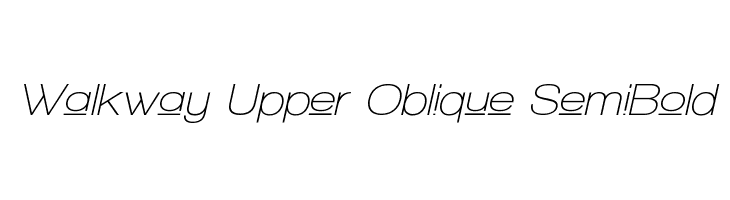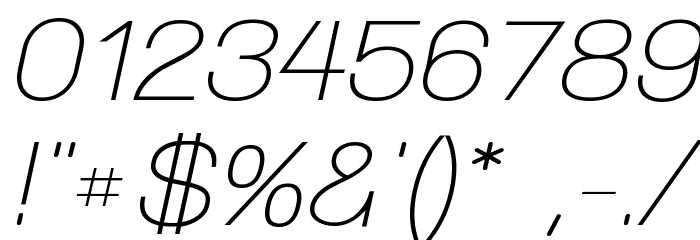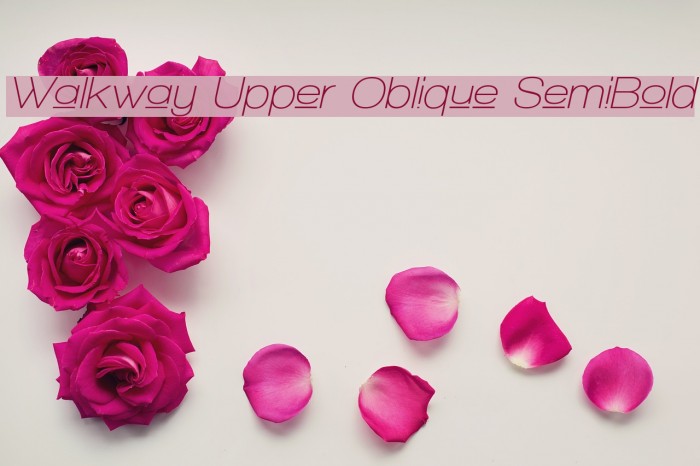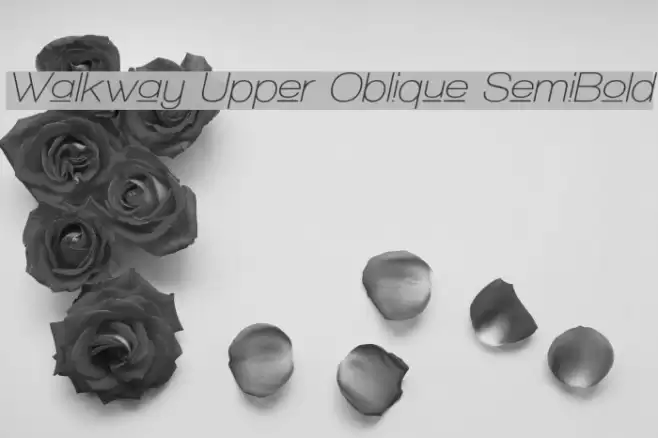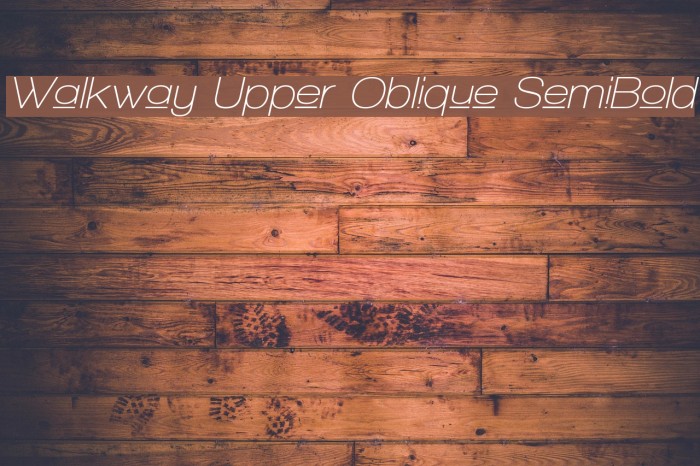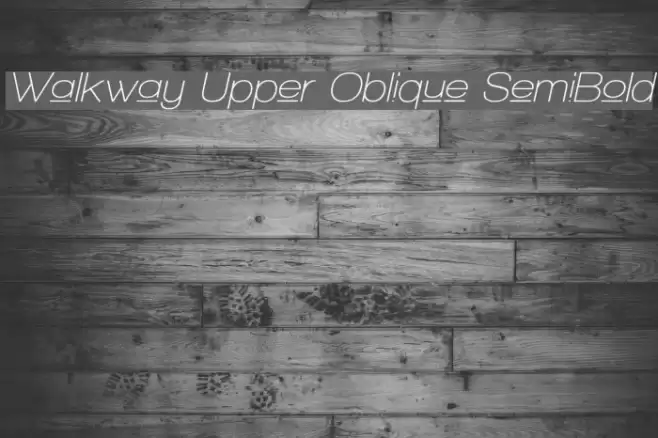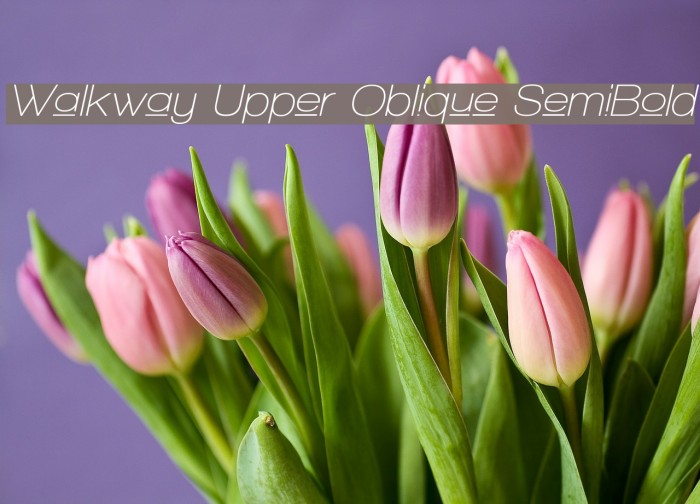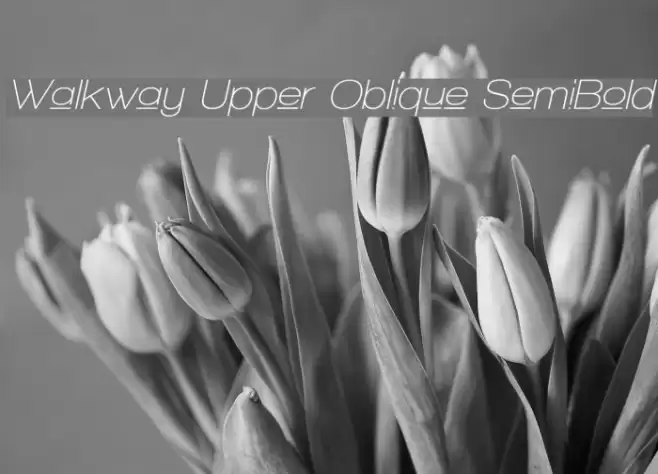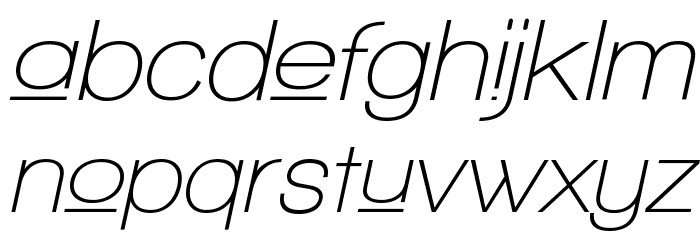
Walkway Upper Oblique SemiBold Font
| 用途 | Headlines, Logos, Branding |
| おすすめプロジェクト | Ideal for branding, advertising, and editorial design where a modern and sleek appearance is desired. |